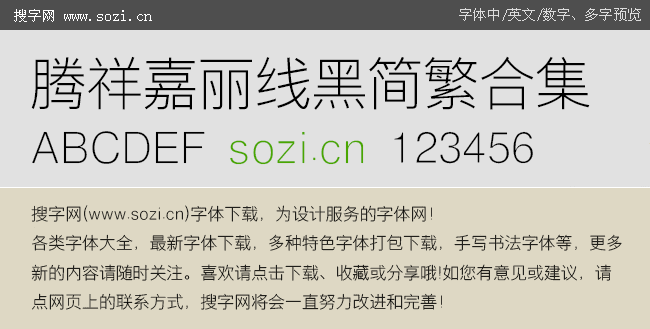
騰祥嘉麗線黑簡(jiǎn)繁合集
搜字網(wǎng)提供一款騰祥嘉麗線黑簡(jiǎn)繁合集中文字體下載,騰祥嘉麗線黑是一款端正的黑體字體,該字體大方得體,整體效果出眾,并且字庫(kù)完整,可用于藝術(shù)設(shè)計(jì)、包裝印刷、簽名設(shè)計(jì)、圖形設(shè)計(jì)等領(lǐng)域。